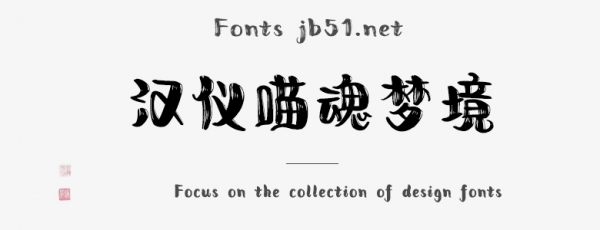
漢儀喵魂夢(mèng)境簡(jiǎn)/繁是由漢儀字庫(kù)出品,字體筆觸粗實(shí),筆畫隨性,具有很好的視覺感,適合應(yīng)用于藝術(shù)設(shè)計(jì)、平面宣傳設(shè)計(jì)、網(wǎng)頁(yè)設(shè)計(jì),書法字帖等領(lǐng)域,需要的朋友可以前來(lái)本站下載。